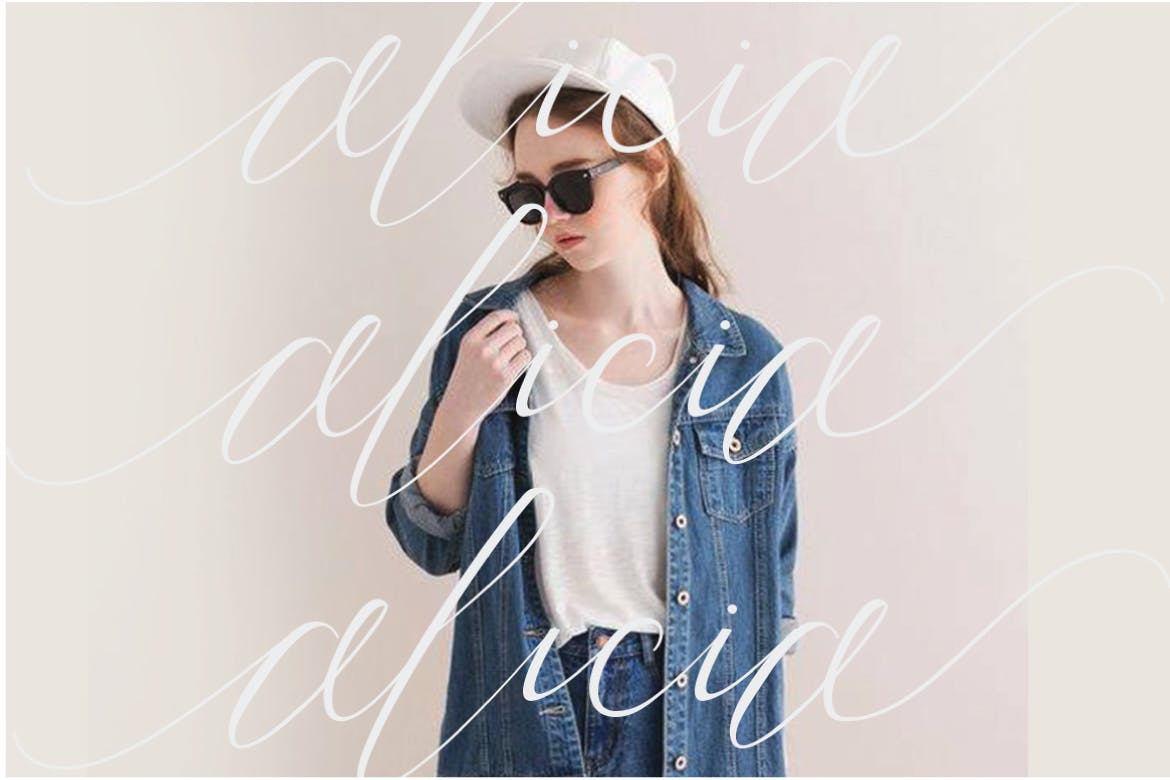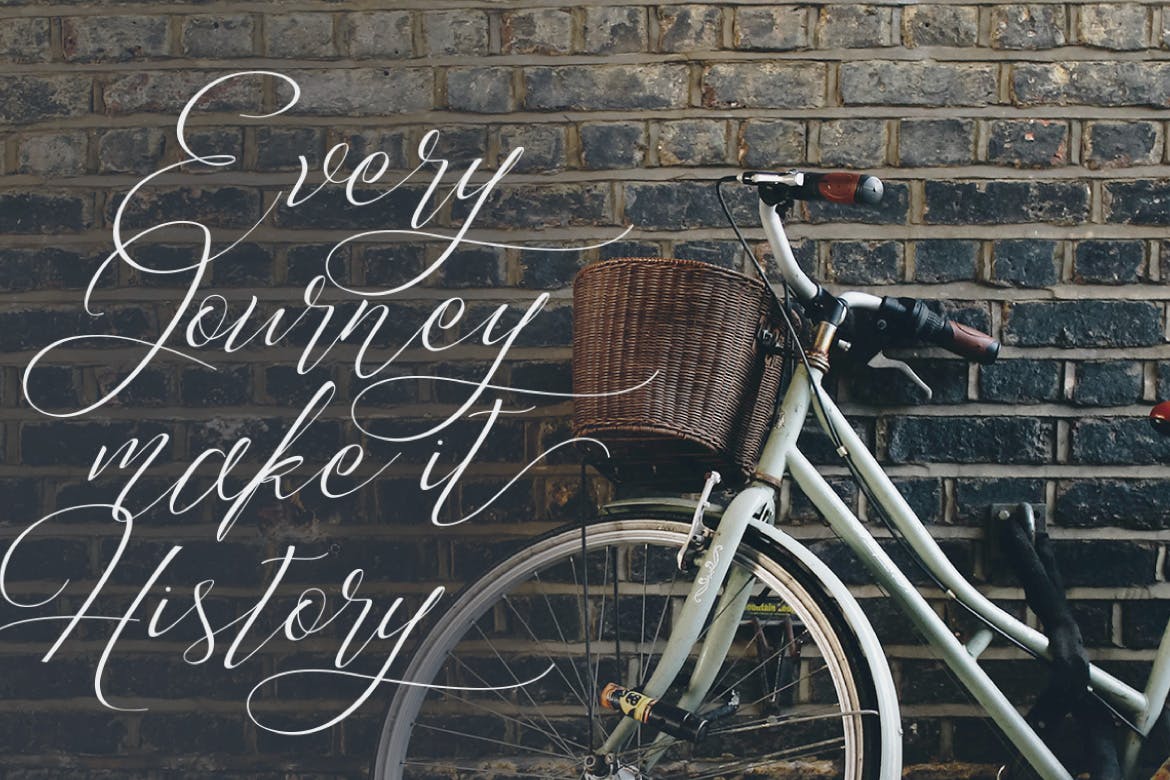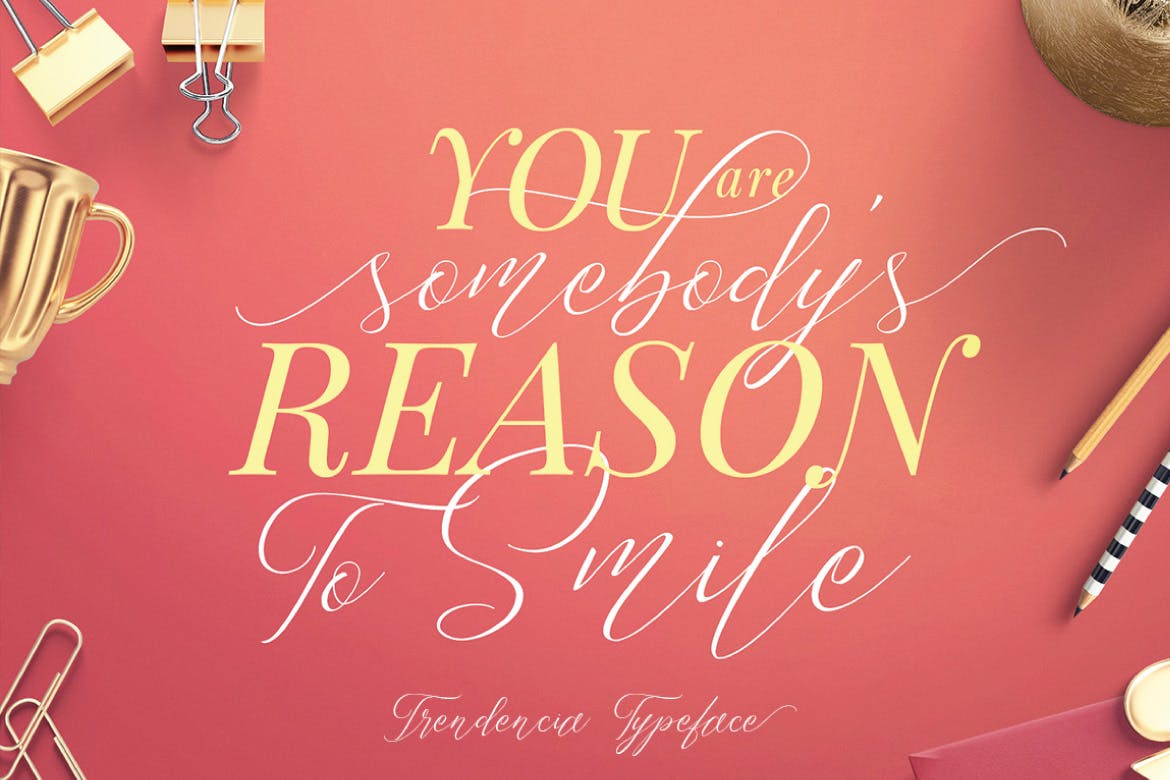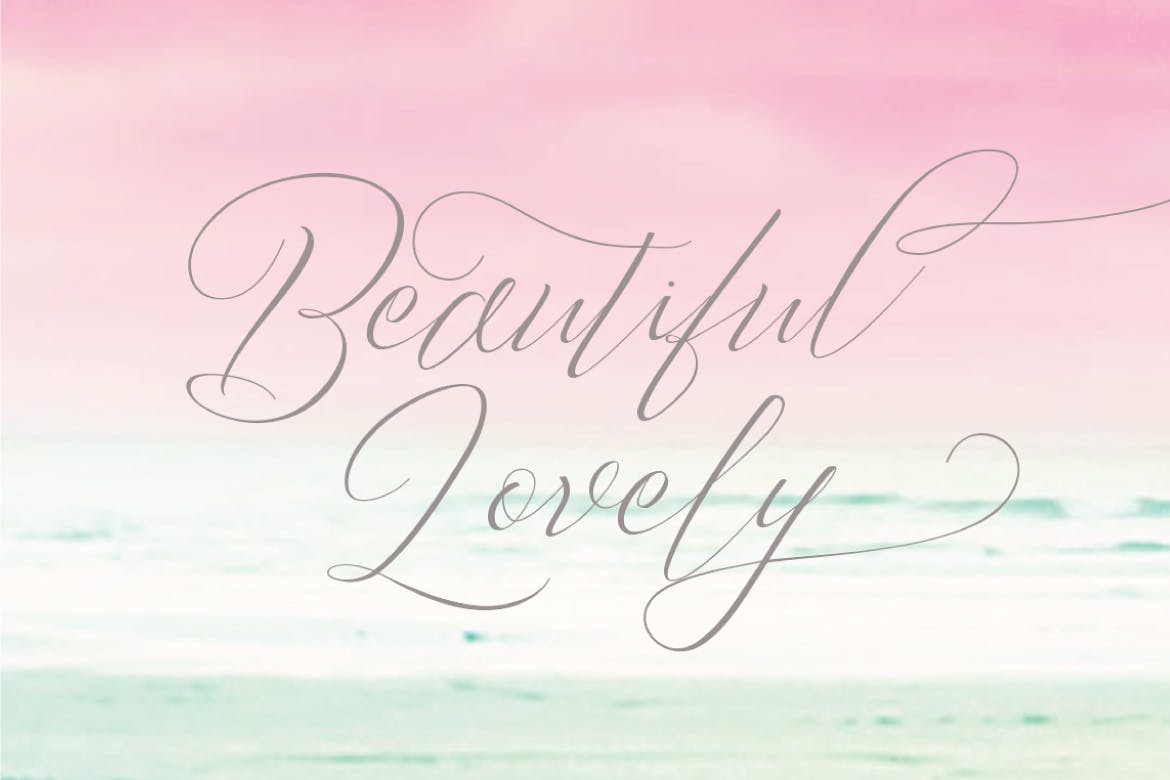
فونت Trendencia Script یک فونت خوشنویسی شیک است که دارای بیسلاین متغیر، خطوط نرم و لمسهای کلاسیک و باوقار میباشد. این فونت برای کاربردهای مختلفی مانند عنوانها، امضا، لوگو، دعوتنامههای عروسی، تیشرت، سربرگ، تابلو، برچسب، اخبار، پوسترها و نشانها قابل استفاده است.